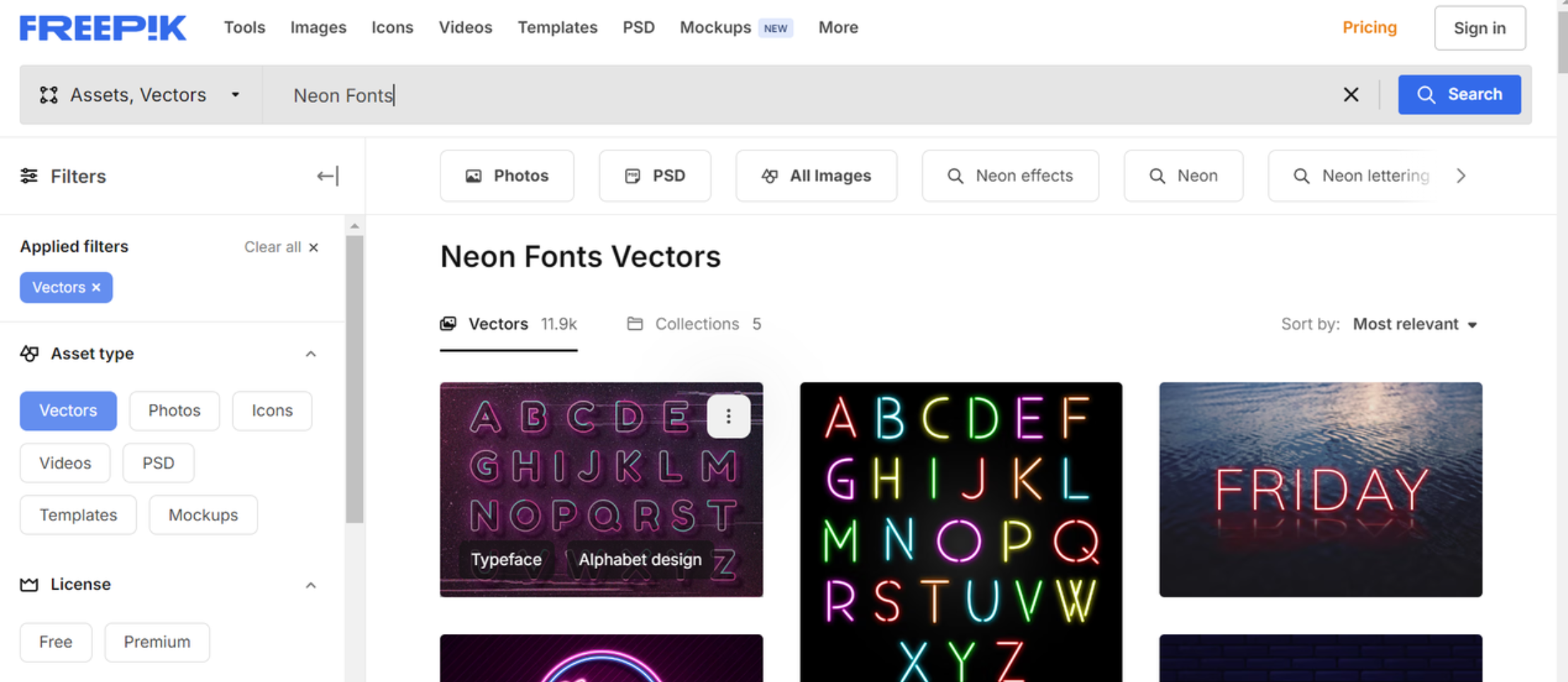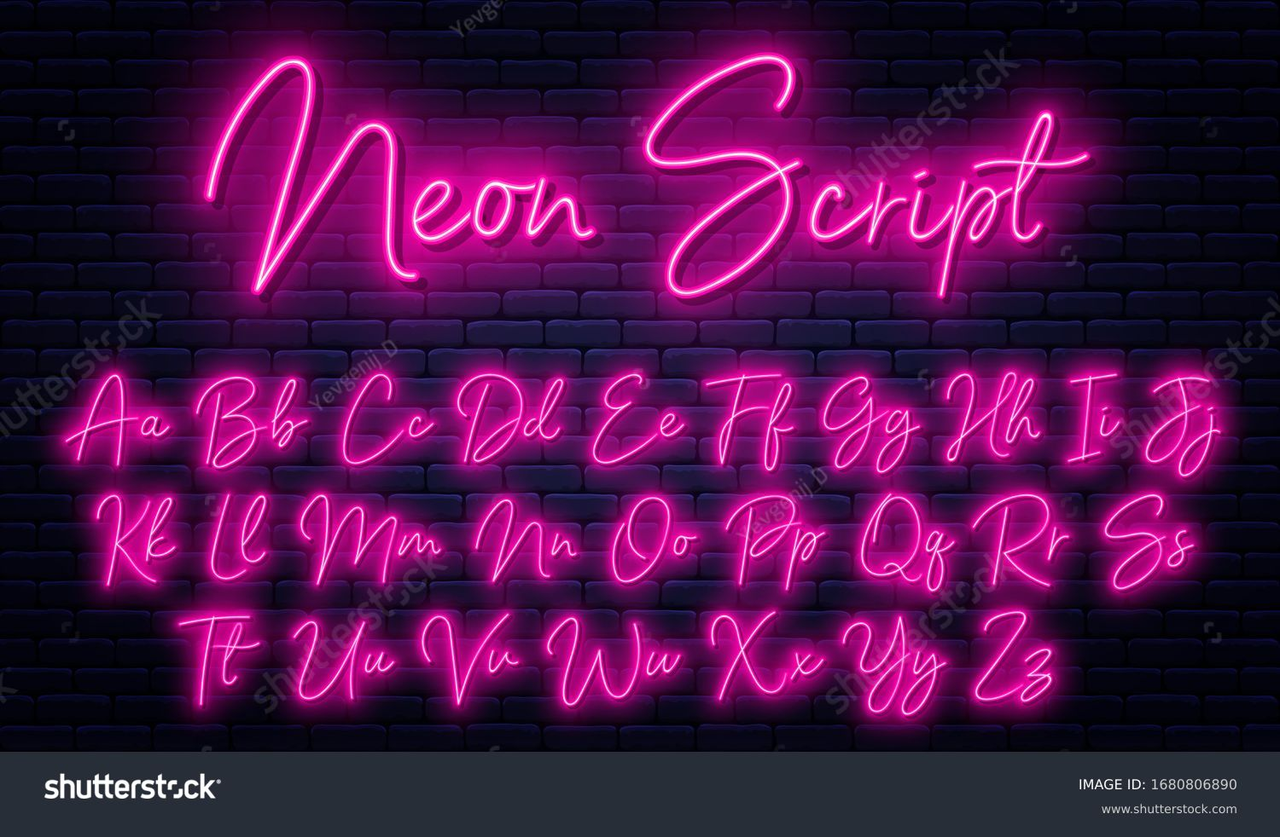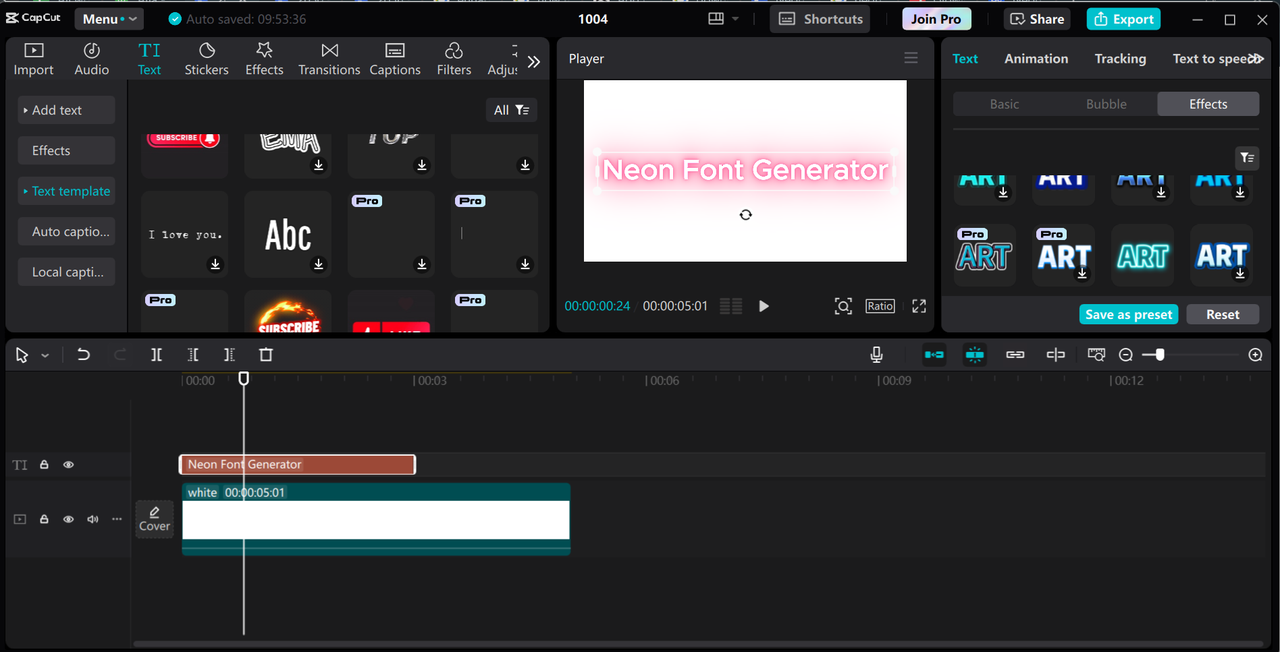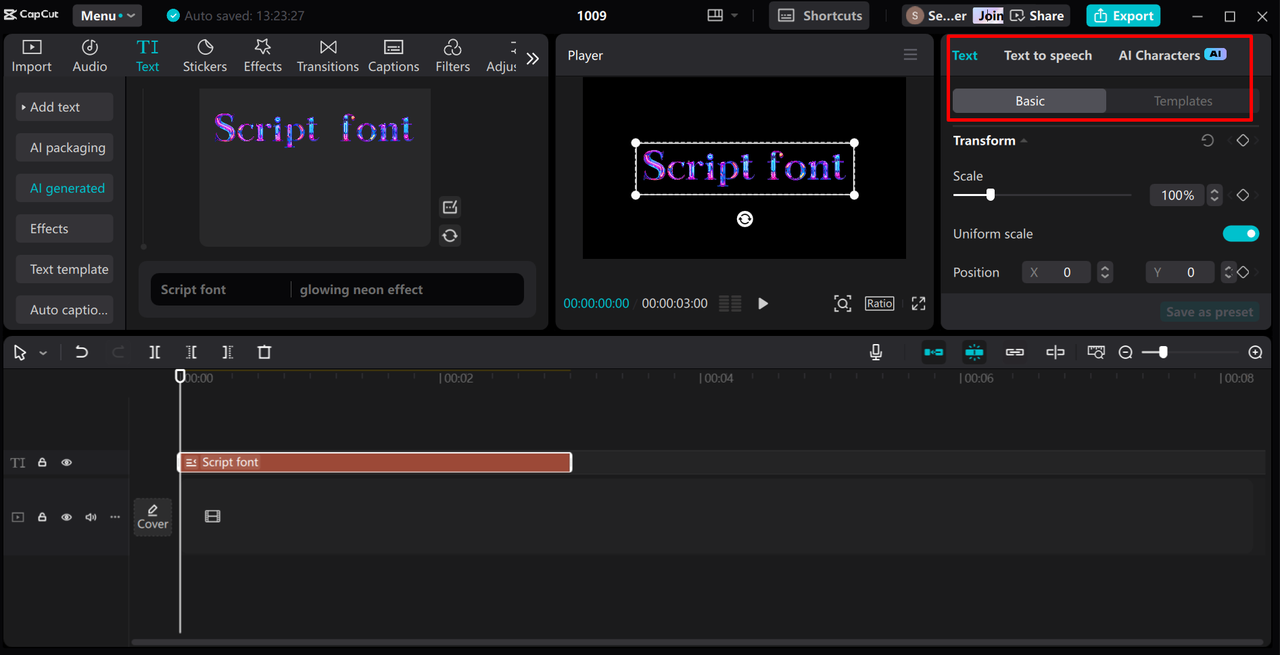
ابحث عن خطوط نيون مجانية لتنزيلها ، وأضف تأثيرًا متوهجًا إلى النص الخاص بك ، واجعل تصميماتك تنبثق. مثالي للشعارات ومنشورات الوسائط الاجتماعية والتصاميم. علاوة على ذلك ، استخدم CapCut لإنشاء خطوط نيون مخصصة ودمجها بسهولة في مقاطع الفيديو الخاصة بك.
النيون الخط مجانا
إذا كنت تريد أن تبرز تصميماتك ، فإن خطوط النيون هي طريقة ممتعة وملفتة للنظر لإضافة لمسة نابضة بالحياة ومتوهجة. يمكن لهذه الخطوط أن تجعل أي محتوى بارزًا ، سواء كان ذلك لوسائل التواصل الاجتماعي أو مواقع الويب أو غيرها من المشاريع الإبداعية. أفضل جزء ؟ يمكنك العثور على الكثير من المصادر الرائعة التي تقدم خطوط نيون مجانًا.
لذلك ، في هذا الدليل ، سوف نستكشف أفضل الأماكن لاكتشاف خطوط النيون المجانية التي ستضفي إشراقة على تصميماتك.
ما هو خط النيون
خط النيون هو نمط نصي مصمم ليشبه إلى حد كبير إشارات النيون المتوهجة بألوان زاهية وحيوية وحواف ناعمة ومضاءة تثير أجواء مفعمة بالحيوية. إنه يخلق تأثيرًا مرئيًا مذهلاً ، غالبًا ما يستخدم لتحسين التصميمات بأجواء حديثة أو قديمة أو مستقبلية تجذب انتباه المشاهد. يعد نمط الخط هذا مثاليًا لجذب الانتباه وإعطاء المحتوى مظهرًا ديناميكيًا وحيويًا ، مما يجعله مثاليًا للإعلان والأحداث والمشاريع الفنية.
Image showing neon font
أنواع خطوط النيون
الآن بعد أن عرفت ما هي خطوط النيون ، دعنا نستكشف الأنواع المختلفة المتاحة. يوفر كل نوع أسلوبًا فريدًا ، من التصميمات الجريئة والمتوهجة إلى التصميمات الأنيقة والحديثة.
• الرجعية النيون
تضفي خطوط النيون الرجعية إحساسًا عتيقًا بأحرف مشرقة وجريئة تشبه خطوط إشارات النيون القديمة من الماضي ، وغالبًا ما تُرى في المطاعم ودور السينما. هذه الخطوط مثالية لإضافة لمسة حنين إلى تصميماتك وتعمل بشكل رائع مع السمات الكلاسيكية ، خاصة عندما تهدف إلى الحصول على مظهر قديم وخالد.
• مخطط النيون
الخطوط العريضة لخطوط النيون لها تأثير متوهج حول حواف الحروف ، مما يترك الداخل مجوفًا ومضيئًا. هذا يخلق مظهرًا نظيفًا وعصريًا ، مثاليًا للتصاميم المستقبلية أو البسيطة التي تمنح نصك مظهرًا مشرقًا وأنيقًا.
• النيون المكتوب بخط اليد
تحاكي خطوط النيون المكتوبة بخط اليد مظهر النص المتوهج المكتوب بخط اليد. يضيف أسلوبها المتدفق غير الرسمي لمسة شخصية وفنية ، مما يجعلها مثالية للمشاريع الإبداعية. تضفي هذه الخطوط الدفء والفردية على أي تصميم ، مما يعزز تفرده وسحره.
• السيناريو متوهجة
يوفر خط النص النيون المتوهج أحرفًا أنيقة ومخطوطة تبدو وكأنها تتألق مع توهج نيون ناعم. إنها رائعة لإضافة تأثير أنيق وأنيق إلى النص الخاص بك مع إبقائه نابضًا بالحياة. مثالية للدعوات أو العلامات التجارية أو أي مشروع ، فهي تضفي لمسة من الرقي والذوق على تصميماتك.
• 3D النيون
تخلق خطوط النيون ثلاثية الأبعاد مظهرًا واقعيًا ثلاثي الأبعاد يجعل النص يخرج من الشاشة. بفضل تأثيرها المتوهج وعمقها ، فإنها تمنح تصميماتك مظهرًا جريئًا يجذب الانتباه. مثالية للإعلانات أو المواد الترويجية ، هذه الرسائل تعزز الرؤية والمشاركة.
١ - فريبيك
Freepik هو مورد رائع لأي شخص يبحث عن خطوط محرف نيون مجانية. يوفر مجموعة متنوعة من التصميمات الأنيقة التي يمكن أن تعزز مشاريعك. سواء كنت بحاجة إلى مظهر مرح أو شيء أكثر أناقة ، يمكنك العثور على خط النيون المثالي هنا. مع سهولة التنقل والكثير من الخيارات ، يجعل Freepik من السهل تفتيح المحتوى الخاص بك.
السمات الرئيسية
• مجموعة واسعة من الخطوط
يوفر Freepik مجموعة واسعة من الخطوط ، والتي تشمل خطوط النيون التي تجعل من السهل العثور على الخط المناسب لأي مشروع تصميم.
• رسومات عالية الجودة
بالإضافة إلى الخطوط ، يوفر Freepik متجهات من الدرجة الأولى ورسوم توضيحية وصور تضمن مجموعة كاملة من الموارد لتصميماتك.
• واجهة سهلة الاستخدام
يجعل التصميم البديهي للمنصة من السهل تصفح الخطوط والرسومات والبحث عنها وتنزيلها مما يوفر الوقت للمستخدمين.
• خيارات مجانية ومتميزة
يوفر Freepik كلاً من التنزيلات المجانية والموارد المتميزة التي تمنح المستخدمين المرونة للاختيار حسب احتياجات مشروعهم.
• تحديثات منتظمة
تتم إضافة خطوط وموارد رسومية جديدة بشكل متكرر ، بحيث يمكن للمستخدمين دائمًا العثور على محتوى جديد ومحدث لتصميماتهم.
Interface of Freepik - a standard website to download neon fonts for free
2. محرر فيديو CapCut: الأفضل لإنشاء خطوط نيون لمقاطع الفيديو
يعد محرر فيديو سطح المكتب CapCut أداة ممتازة لإضافة خطوط نيون إلى مقاطع الفيديو الخاصة بك. بفضل ميزاته سهلة الاستخدام ، يمكنك إنشاء نص لافت للنظر ينبثق من الشاشة. يتيح لك هذا البرنامج تخصيص الألوان والأحجام والأنماط لتتناسب مع أجواء الفيديو الخاص بك. سواء كنت تقوم بمونتاج ممتع أو عرض تقديمي احترافي ، يساعدك CapCut على تفتيح المحتوى الخاص بك باستخدام خطوط نيون مذهلة.
Editing interface of the CapCut desktop video editor - the best free neon font generator
السمات الرئيسية
• بنقرة واحدة الجيل الخط
يسمح لك CapCut بإنشاء خطوط نيون بنقرة واحدة فقط. إنه مثالي لأولئك الذين يريدون نتائج فورية لإنشاء شعارات نيون .
• مكتبة من الخطوط النيون مسبقة الصنع
يوفر المحرر مجموعة غنية من خطوط النيون المصممة مسبقًا والتي توفر الكثير من الخيارات لمقاطع الفيديو الخاصة بك. يمكنك بسهولة تصفح الأنماط المختلفة للعثور على التطابق المثالي لترجمة الفيديو والمشاريع الأخرى.
• الخطوط العريضة بسهولة سمك الخط
يعد ضبط سمك الخطوط العريضة لخط النيون أمرًا بسيطًا باستخدام عناصر تحكم سهلة الاستخدام. يتيح لك هذا التخصيص إبراز النص تمامًا كما تريد.
• تأثيرات البرق للنص
يمكنك إضافة تأثيرات إضاءة ديناميكية لتحسين خطوط النيون الخاصة بك ، مما يمنحها توهجًا مثيرًا. يضيف عنصرًا مرئيًا مثيرًا يمكن أن يأسر جمهورك.
• الظلال قابل للتعديل لخطوط النيون
في CapCut ، يعد تعديل الظلال خلف نص النيون واضحًا ويضيف عمقًا وأبعادًا. تساعد هذه الإمكانية في إنشاء مظهر أكثر واقعية وجاذبية لتصميماتك.
كيفية إنشاء خطوط النيون باستخدام AI في CapCut
لإنشاء خطوط نيون باستخدام AI في CapCut ، قم أولاً بتنزيل البرنامج باستخدام الزر أدناه إذا لم يكن مثبتًا بالفعل. أكمل عملية التثبيت ، وبعد ذلك يمكنك إنشاء نص نيون نابض بالحياة لمقاطع الفيديو الخاصة بك.
STEP 1
1. إنشاء خط النيون مع AI
انتقل إلى علامة التبويب النصية وحدد "AI created". أدخل مطالبتك ووصف تأثير النيون الذي تريد إنشاءه لخطك. اختر نمط الخط من خيار "ضبط" ، ثم انقر فوق "إنشاء".
Creating neon font in the CapCut desktop video editor
STEP 2
1. تخصيص وإضافة الخط
بعد إنشاء الخط ، اضبط حجمه ووضعه بالضبط في المكان الذي تريد أن يظهر فيه النص في الفيديو الخاص بك. الآن ، قم بدمج هذا النص الذي تم إنشاؤه في مقاطع الفيديو الخاصة بك وقم بتحريره باستخدام أدوات متقدمة.
Customizing and adding neon font in the CapCut desktop video editor
STEP 3
1. تصدير وحصة
انقر فوق الزر "تصدير" واضبط الإعدادات ، بما في ذلك الدقة ومعدل البت وبرنامج الترميز والتنسيق ، لتناسب احتياجاتك. احفظه على جهازك ، أو يمكنك أيضًا استخدام خيار "مشاركة" لتحميل الفيديو الخاص بك مباشرة إلى TikTok أو YouTube.
Exporting a video with neon effect from the CapCut desktop video editor
3. فونتسبيس
Fontspace عبارة عن منصة شهيرة تقدم مجموعة كبيرة من خطوط نصوص النيون المجانية. إنه مثالي للمصممين الذين يبحثون عن طباعة إبداعية وفريدة من نوعها تعزز مشاريعهم. يسهل التنقل في الموقع ويجعل اكتشاف الخطوط بسيطًا وفعالًا. مع توفر آلاف الخطوط ، يساعد Fontspace المستخدمين في العثور على الخط المثالي لأي مشروع إبداعي.
السمات الرئيسية
• مكتبة الخطوط الضخمة
يوفر فونتسبيس الوصول إلى أكثر من 100 ، 000 الخطوط الحرة ، والتي تمكنك من العثور على النمط المناسب لأي حاجة التصميم.
• سهولة البحث والتصفية
يمكنك البحث بسرعة عن الخطوط حسب النمط أو الفئة أو الشعبية ، مما يجعل من السهل تحديد موقع الخط المثالي في ثوانٍ.
• مجاني للاستخدام التجاري
يوفر Fontspace مجموعة واسعة من خطوط النيون المجانية للاستخدام التجاري ، مما يمنحك المرونة لدمجها في مشاريع مختلفة دون قيود.
• مساهمات المصمم
يتميز الموقع بخطوط ساهم بها مصممون محترفون تضمن مجموعة متنوعة من خيارات الطباعة عالية الجودة.
Interface of Fontspace -  the best website to download neon script font for free
4 - فونتس (ج)
Fontsc عبارة عن منصة متعددة الاستخدامات توفر مجموعة متنوعة من الخطوط المجانية التي تلبي جميع احتياجات التصميم. يتميز بمجموعة متنوعة رائعة من الأساليب التي تتضمن خطوط نيون لافتة للنظر. يحتوي موقع الويب على تخطيط واضح يجعل من السهل على الزائرين تحديد موقع الطباعة الذي يريدونه بسرعة. مع الالتزام بالجودة ، يضمن Fontsc وصول المصممين إلى أفضل الخطوط المتاحة.
السمات الرئيسية
• أنماط الخطوط المتنوعة
يوفر Fontsc مجموعة واسعة من أنماط الخطوط ، والتي تشمل تصميمات مرحة وأنيقة وحديثة ، وتضمن وجود شيء لكل مشروع.
• ميزة المعاينة
قبل التنزيل ، يمكن للمستخدمين معاينة كيف سيبدو نصهم بخطوط مختلفة ، مما يساعدهم على اتخاذ خيارات مستنيرة لتصميماتهم.
• مجانا بالنسبة لنا التجارية
معظم خطوط النيون مجانية أيضًا للاستخدام التجاري ، مما يجعلها موردًا قيمًا ليس فقط للمشاريع الشخصية ولكن أيضًا للمحترفين والطلاب والهواة على حد سواء.
• مساهمات المجتمع
يسمح Fontsc للمصممين بمشاركة خطوطهم ويخلق بيئة تعاونية تحافظ على مجموعة الخطوط جديدة ومثيرة.
Interface of Fontsc -  a reliable website to get neon light font free download
5 - فونتسك
Fontesk عبارة عن منصة راسخة توفر مجموعة واسعة من الخطوط عالية الجودة ، والتي تتضمن مجموعة متنوعة من الخيارات الإبداعية ، مثل خط النيون النصي المجاني. بفضل تصميمه البديهي ، يتيح Fontesk للمستخدمين استكشاف الخطوط وتنزيلها وفقًا لمشروعهم. هذه المنصة مثالية لإيجاد أنماط طباعة فريدة ومهنية تعزز تصميماتك.
السمات الرئيسية
• تشكيلة واسعة من الطباعة
تقدم Fontesh مجموعة واسعة من أنماط الطباعة ، والتي تشمل نصوصًا أنيقة وشاشات جريئة وخيارات نيون نابضة بالحياة ، تلبي احتياجات التصميم المختلفة.
• سهولة التصفح
تم تصميم موقع الويب للتصفح المباشر ، والذي يسمح للمستخدمين بالعثور على الخطوط حسب الفئات أو الأنماط بسرعة.
• تحميل بدون تسجيل
يمكن للمستخدمين تنزيل الخطوط بسهولة دون الحاجة إلى إنشاء حساب ، مما يجعل العملية سريعة وفعالة.
• اقتراحات اقتران الخط
يوفر Fontesk اقتراحات مفيدة لأزواج الخطوط ويساعد المصممين في اختيار الأنماط التكميلية للتصاميم المتماسكة.
Interface of Fontesk -  the best website to get free neon fonts for commercial use
استخدام حالات الخط ضوء النيون مجانا
بعد استكشاف مكان العثور على خطوط ضوء النيون وتنزيلها مجانًا ، من المهم مراعاة تطبيقاتها العملية. أدناه ، ناقشنا أين يمكنك استخدام هذه الخطوط:
• منشورات وسائل التواصل الاجتماعي
يمكن لخطوط ضوء النيون المجانية أن تجعل مشاركاتك على وسائل التواصل الاجتماعي أكثر جاذبية وجاذبية. إنها تساعد المحتوى الخاص بك على التميز في الخلاصات المزدحمة التي تجذب المزيد من الإعجابات والمشاركات. يضيف استخدام هذه الخطوط لمسة ممتعة ونابضة بالحياة إلى رسائلك.
• نشرات الحدث
يؤدي دمج خطوط النيون في منشورات الأحداث إلى إثارة الإثارة وجذب الانتباه بسرعة. يمكن للأنماط المشرقة والجريئة أن تنقل بشكل فعال طاقة الحدث الخاص بك ، سواء كان حفلة موسيقية أو حفلة أو مهرجان. هذا يسهل على الناس التذكر والرغبة في الحضور.
• الصور المصغرة على YouTube
يمكن أن يؤدي استخدام خطوط ضوء النيون في الصور المصغرة على YouTube إلى زيادة ظهور الفيديو بشكل كبير. تجذب الألوان الزاهية والأنماط الفريدة المشاهدين وتشجعهم على النقر والمشاهدة. يساعد المحتوى الخاص بك على أن يبدو أكثر احترافًا وجاذبية.
• دعوات الحزب
تضفي خطوط النيون إحساسًا حيويًا على دعوات الحفلات ، مما يحدد نغمة الاحتفال الممتع. يمكن أن تعكس موضوع الحدث الخاص بك ، مما يجعل الضيوف متحمسين للحضور. تضيف الأنماط النابضة بالحياة لمسة شخصية تجعل دعواتك لا تُنسى.
• شعارات العلامة التجارية
يمنح دمج خطوط ضوء النيون في شعارات العلامة التجارية عملك مظهرًا عصريًا وحيويًا. يمكن أن يساعد هذا النمط الفريد علامتك التجارية على التميز في سوق تنافسية. يمكن لشعار النيون المصمم جيدًا أن يترك انطباعًا دائمًا لدى العملاء.
الاستنتاج
في الختام ، يمكن أن يؤدي العثور على خط النيون المثالي إلى تحسين تصميماتك بشكل كبير وإضافة لمسة نابضة بالحياة إلى مشاريعك. مع العديد من المنصات مثل Fontspace و Freepik و Fontesk ، يمكنك تنزيل خطوط النيون مجانًا.
علاوة على ذلك ، لا تنس استخدام محرر فيديو سطح المكتب CapCut ، والذي يُعرف باسم أفضل مولد نصوص نيون مجاني. يمكّنك من دمج هذه الخطوط بسلاسة في مقاطع الفيديو التي تضفي لمسة متوهجة على إبداعاتك.
الأسئلة الشائعة
1
1. هل هناك أي خطوط نيون مجانية للموسيقى ؟
نعم ، هناك العديد من مواقع الويب حيث يمكنك العثور على خط النيون وتنزيله مجانًا. توفر مواقع الويب مثل Freepik و FontSpace مجموعة متنوعة من الخطوط ذات النمط النيون التي يمكن تنزيلها واستخدامها لأغراض شخصية أو تجارية. يمكن لهذه الخطوط تحسين صورك الموسيقية والمواد الترويجية. عندما يتعلق الأمر بإضافة خطوط نيون إلى مقاطع الفيديو الاحترافية ، يمكنك استخدام محرر فيديو سطح المكتب CapCut.
2
1. هل يمكنني إنشاء خط إشارة نيون مجاني باستخدام الذكاء الاصطناعي ؟
نعم ، يُعرف محرر فيديو سطح المكتب CapCut بأنه أفضل مولد خطوط نيون مجاني. يستخدم AI لإنشاء خطوط إشارة نيون عن طريق إدخال موجه بسيط. بمجرد إنشاء علامة نيون باستخدام AI ، يمكنك تنزيلها بشكل منفصل لاستخدامها على منصات أخرى.